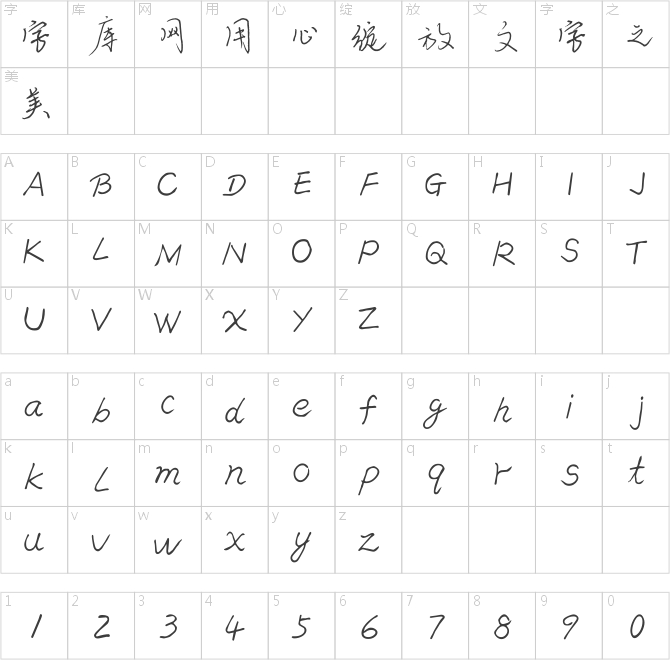
騰祥巧巧手跡簡(jiǎn)
騰祥巧巧手跡簡(jiǎn)字體下載TTQiaoQiaoJ
此款字為騰祥巧巧手跡。書(shū)寫(xiě)一氣呵成,獨(dú)具作者自己的風(fēng)格,無(wú)拘無(wú)束具有不同的視覺(jué)效果,用于正文更體現(xiàn)出手寫(xiě)自然之感。本作品可適用于屏幕顯示、印刷出版、包裝設(shè)計(jì)、廣告設(shè)計(jì)、網(wǎng)頁(yè)設(shè)計(jì)等。
騰祥巧巧手跡簡(jiǎn)字體TTQiaoQiaoJ字庫(kù)是一款讓人賞心悅目、百看不厭的中文字體,適合各類(lèi)廣告和產(chǎn)品包裝設(shè)計(jì)應(yīng)用,字體大小9.15MB,格式為ttf字體,上傳用戶是誠(chéng)澤永信,作者/版權(quán)方為騰祥字庫(kù)